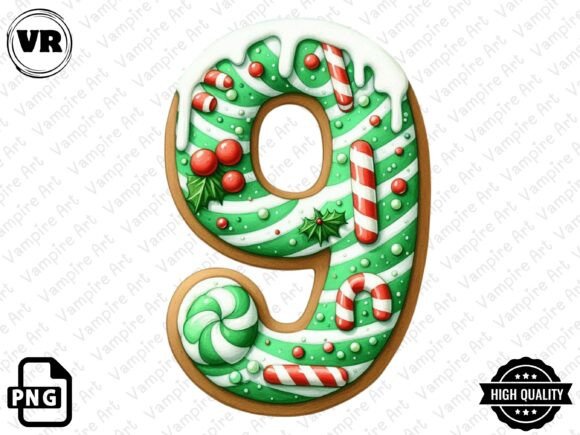
Holiday Typeface and Number Clipart PNG
Mencari elemen reka bentuk yang sesuai boleh menjadi mencabar, tetapi Holiday Typeface and Number Clipart PNG menawarkan koleksi luar biasa yang menaik taraf karya anda serta-merta.
Dicipta dengan ketepatan, Holiday Typeface and Number Clipart PNG menyediakan vektor yang bersih, tipografi yang licin dan lesen komersial untuk ketenangan fikiran.
Sama ada anda mencipta produk POD (Print on Demand), jemputan perkahwinan atau grafik media sosial, Holiday Typeface and Number Clipart PNG amat bersesuaian.